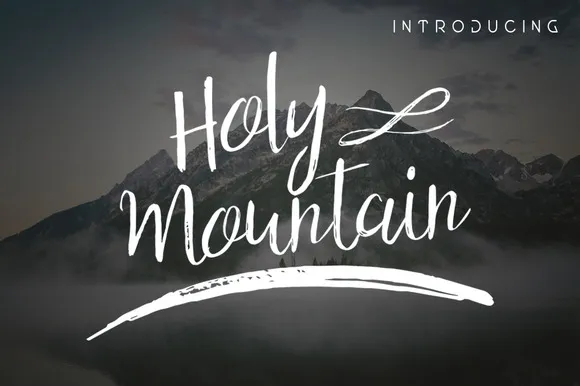
Holy Mountain Script Font – Download Grátis
Esta moderna tipografia script foi cuidadosamente escrita com curvas suaves para criar uma fonte única e distintiva. Holy Mountain é um tipo casual de escrita artística composto por letras maiúsculas e minúsculas, pontuação e números, incluindo alternativas estilizadas. Ideal para seus casamentos, blogs, mídias sociais, citações, impressões, aniversários, cartas, capas de livros e muito mais. Holy Mountain Script Font é perfeito para decorar seu site ou aplicativo com um estilo autêntico e único.